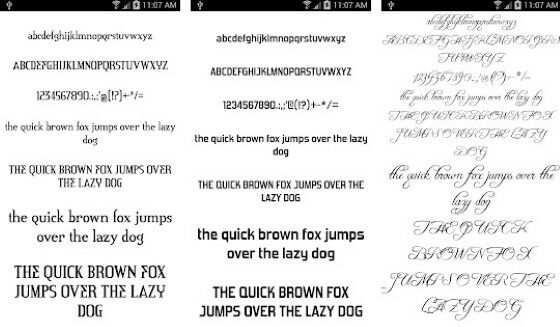
Aplikasi font terbaik dan gratis ini bisa memungkinkanmu mengetik dengan huruf-huruf estetik di HP, apalagi buat kamu yang bosan dengan jenis font yang itu-itu aja.
Seperti yang kamu tahu, HP Android selalu menyajikan jenis font yang membosankan dan bikin bosan buat kamu yang terbiasa dengan huruf-huruf kreatif.
Oleh karena itu, Jaka bakal kasih kamu rekomendasi aplikasi font Android terbaik untuk mengubah font yang ada di handphone kamu.
Rekomendasi Aplikasi Font Android Terbaik
Aplikasi-aplikasi berikut bisa kamu gunakan baik untuk mengubah font pada handphone ataupun menggunakannya untuk posting di media sosial.
1. HiFont
Aplikasi pertama yang akan Jaka bahas adalah HiFont. Aplikasi ini memiliki berbagai jenis font yang lumayan lengkap. Mau yang model unyu, komik, cinta, pink, tulisan tangan, semua ada.
Jika kamu punya font sendiri yang ingin kamu gunakan, kamu bisa mengimpornya, loh. Di dalam aplikasi ini juga telah tersedia emoji yang bisa kamu gunakan.
2. Fonts for FlipFont50 #6
Sesuai dengan namanya, Fonts for FlipFont50 #6 memiliki 50 pilihan font yang berbeda. Aplikasi ini dioptimalkan untuk kamu yang menggunakan handphone Samsung ataupun HTC.
3. FancyKey Keyboard - Cool Fonts
Kalau yang satu ini hanya akan mengubah font pada keyboard handphonemu geng! FancyKey Keyboard akan membuatmu bisa melakukan kustomisasi keyboard sesuai dengan kreativitasmu.
Yang bisa kamu ubah sesuai dengan keinginanmu adalah bentuk, background gambar, efek ketika mengetik, dan tentu saja font keyboard-nya.
Sebenarnya banyak aplikasi keyboard terbaik lainnya yang bisa kamu gunakan, apabila kamu tidak suka dengan aplikasi yang satu ini.
Aplikasi Font Lainnya . . .
4. iFont
Meskipun namanya iFont, aplikasi yang satu ini bukan diproduksi oleh Apple kok geng! Ini hanyalah sebuah aplikasi yang tersedia di Play Store untuk mengubah font pada handphonemu.
Ada banyak sekali jenis font yang bisa kamu gunakan. Apalagi, pihak developer termasuk rajin mengupdate font-font terbaru.
Tidak cukup di situ, kamu juga bisa mengubah warna dan ukuran font yang kamu gunakan. Jangan khawatir jika ada apa-apa karena aplikasi ini juga telah dilengkapi dengan sistem backup.
5. Stylish Fonts
6. Fonts for FlipFont 50 Written
APK font keren ini diproduksi oleh pengembang yang sama dengan aplikasi yang Jaka rekomendasikan nomor 2.
Bedanya, Fonts for FlipFont 50 Written menyediakan macam-macam font yang bergaya tulisan tangan.
Akhir Kata
Itulah ke delapan aplikasi font Android terbaik yang Jaka rekomendasiin untuk kamu agar tampilan handphonemu makin kece.